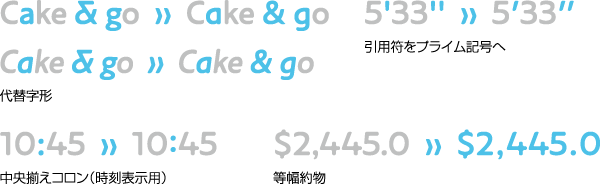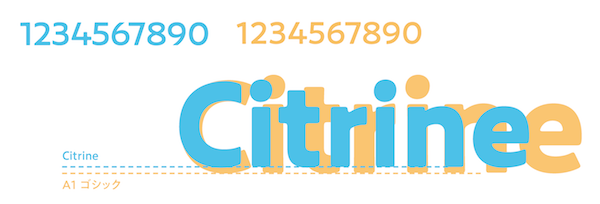
【Citrineについて】
デザインのセット
「Citrine」(シトリン)は、スラッシュ付きゼロや上付き・下付き文字などに加え、さまざまなデザインのセットを備えています。
・セット1:One-storey a and g(aとgの代替字形)
・セット2:Plain Ampersand(&の代替字形)
・セット3:Quotes to Primes(引用符をプライム記号へ)
・セット4:Vertically Centered Colon for Time Display(時刻表示用 中央揃えコロン)
・セット20:Tabular Punctuation(等幅約物)
同じデザインを採用しているA1ゴシックの従属欧文では、より和文と調和するよう、ふところの使い方やデザインに変更を加えています。
Citrineの対応言語